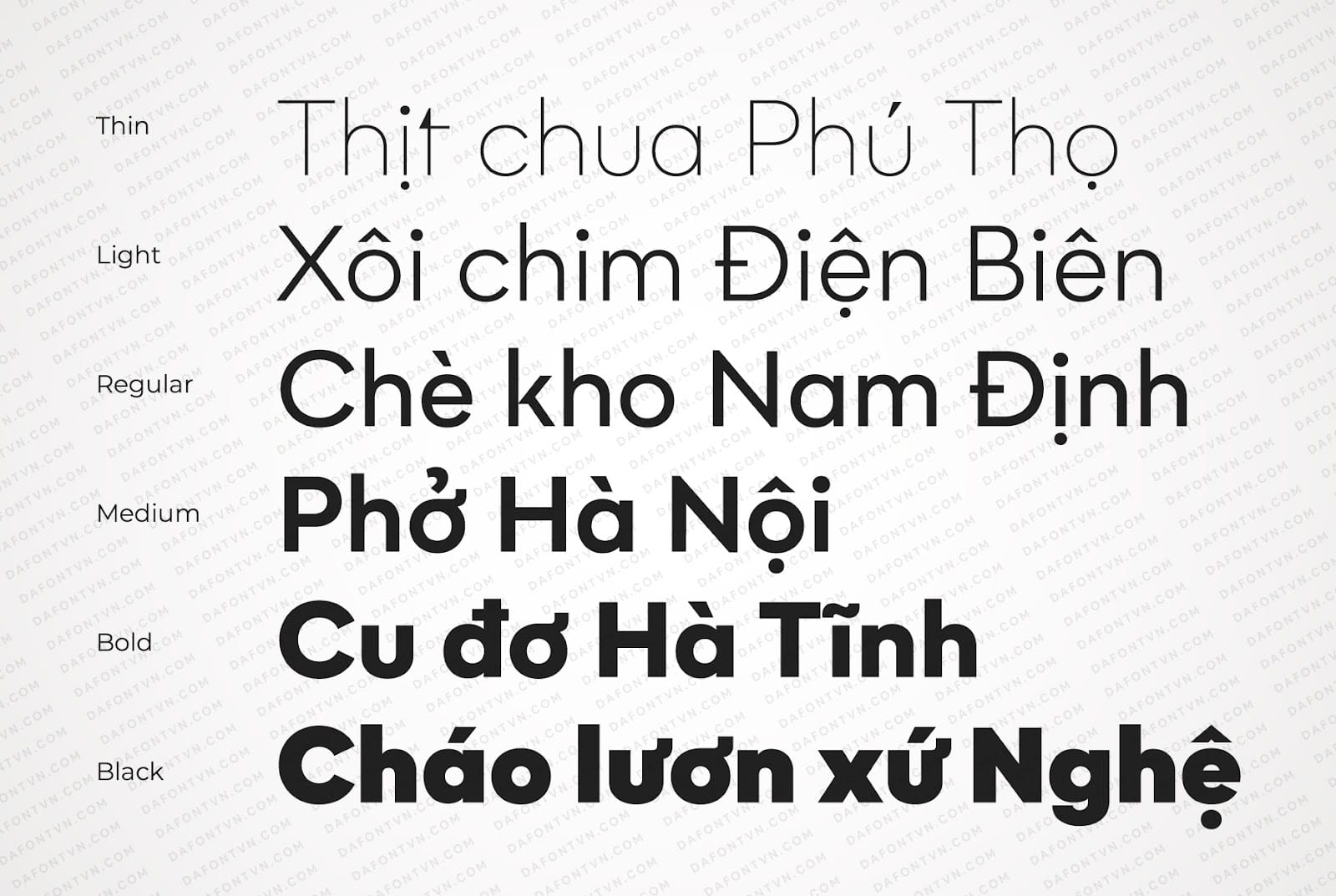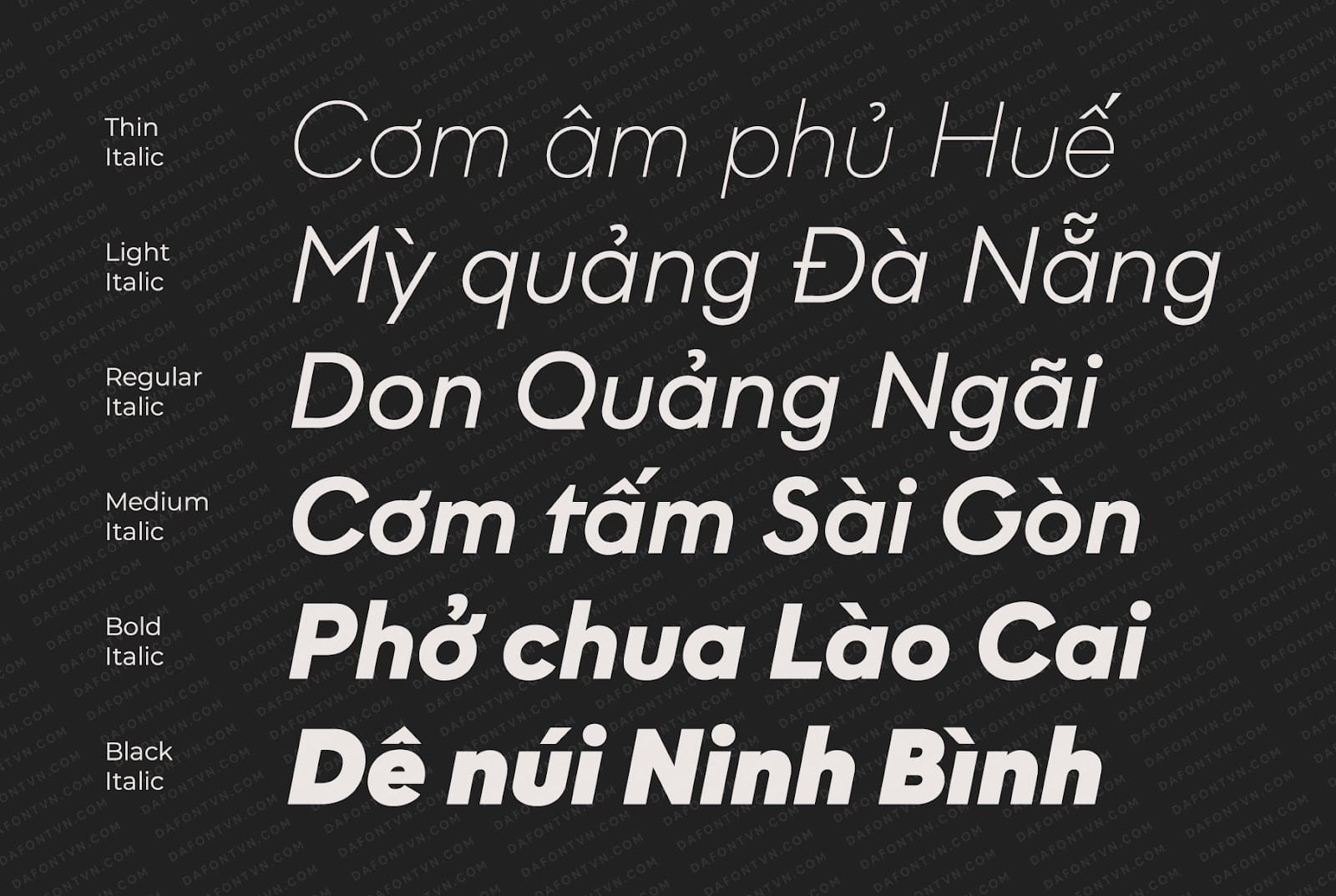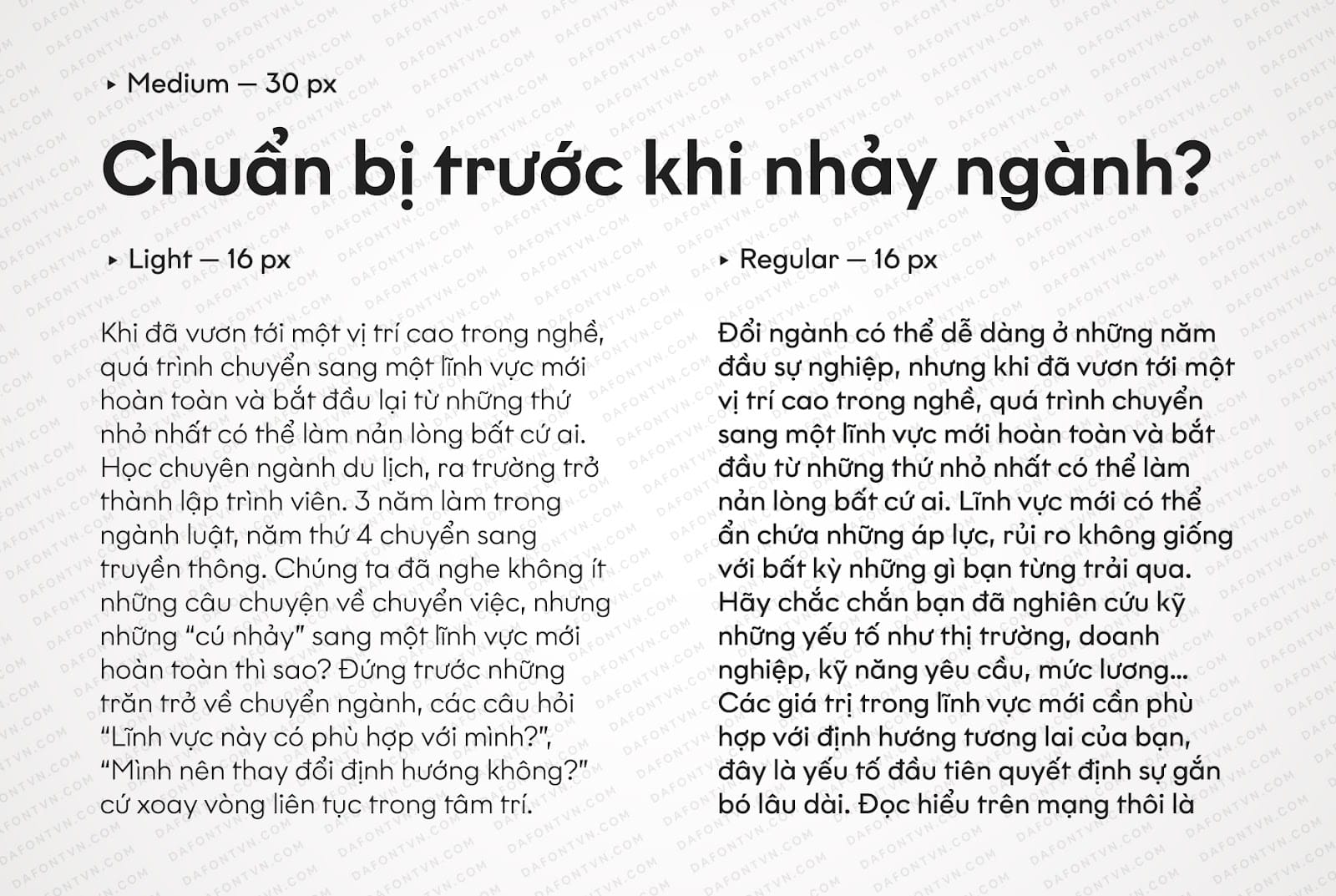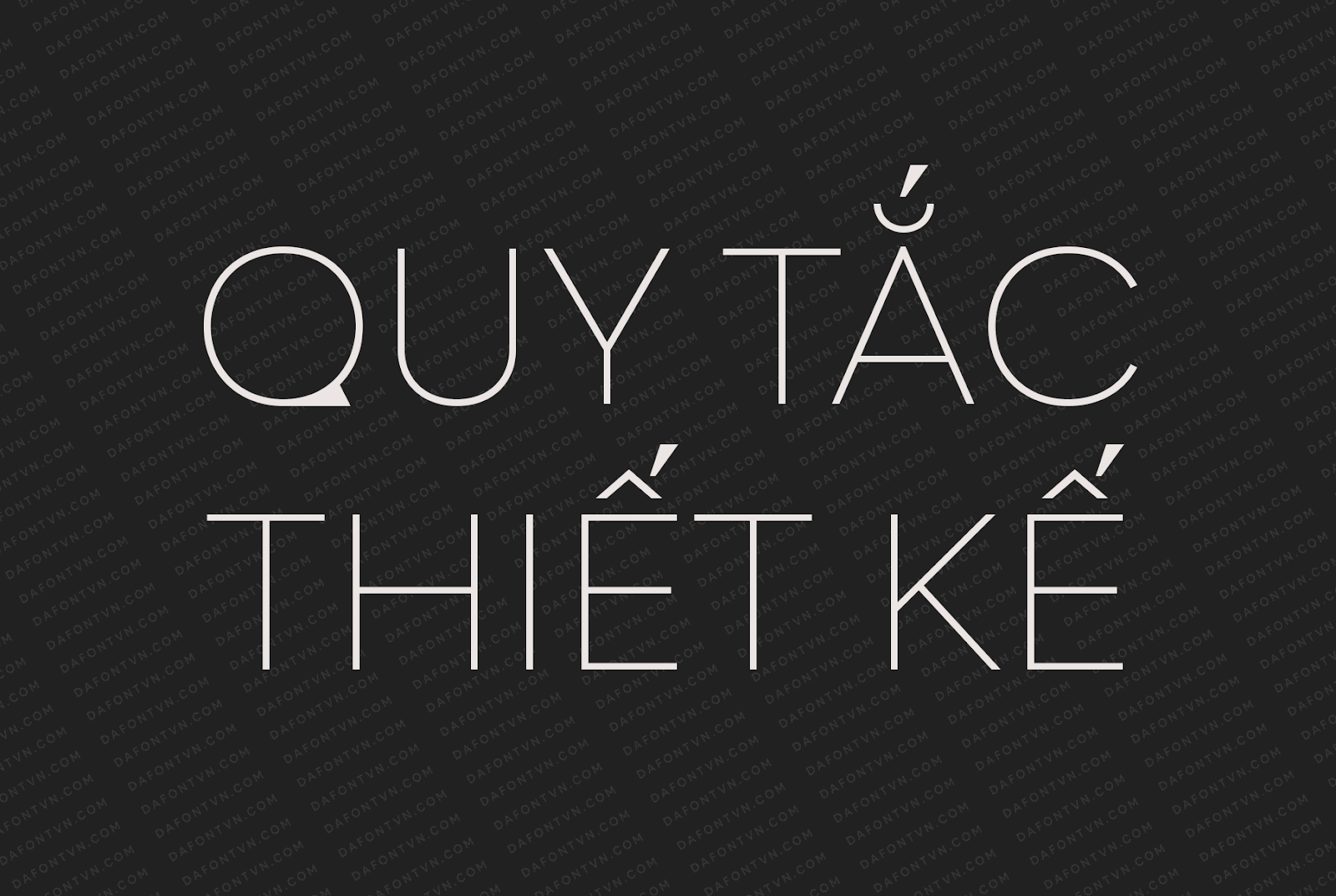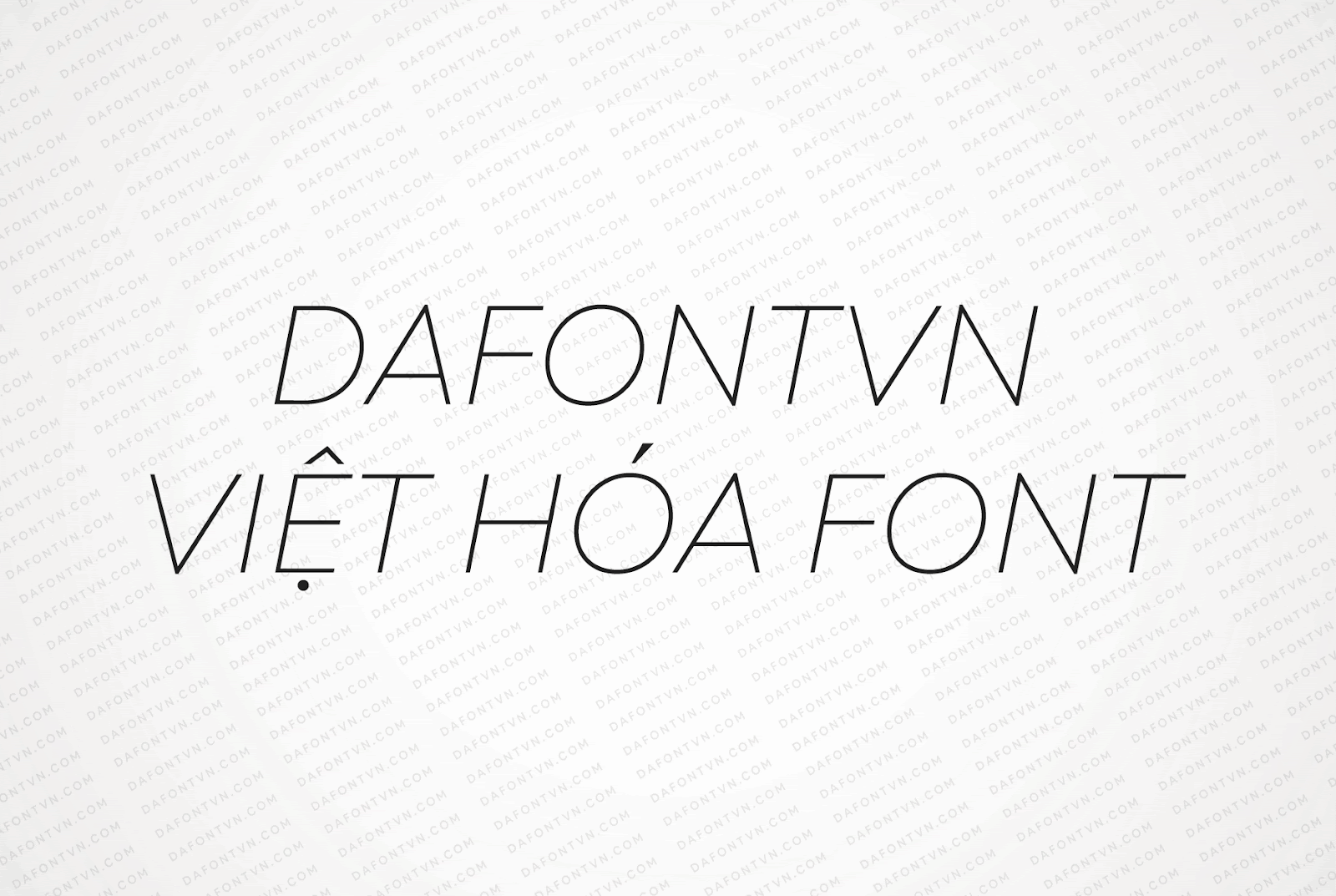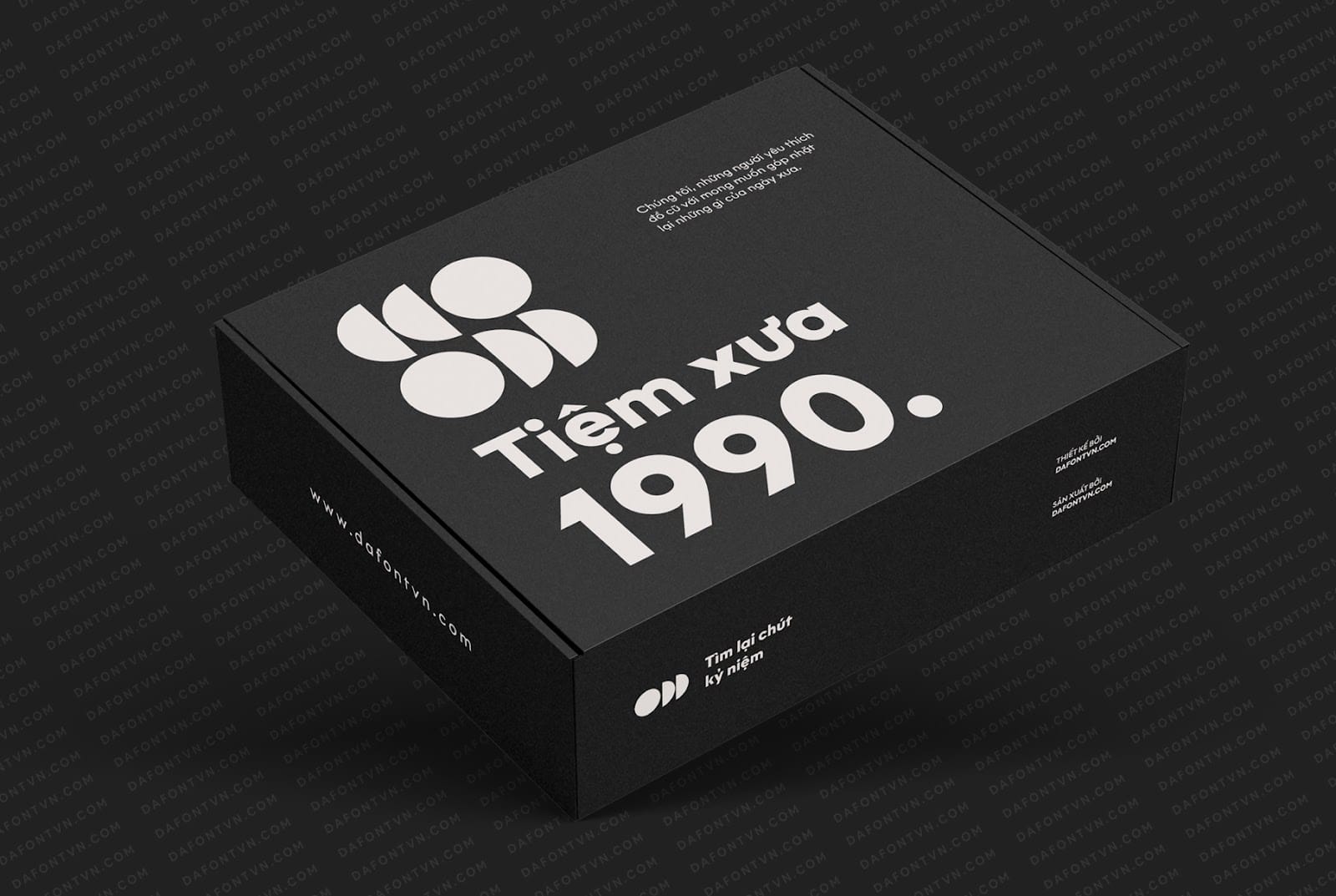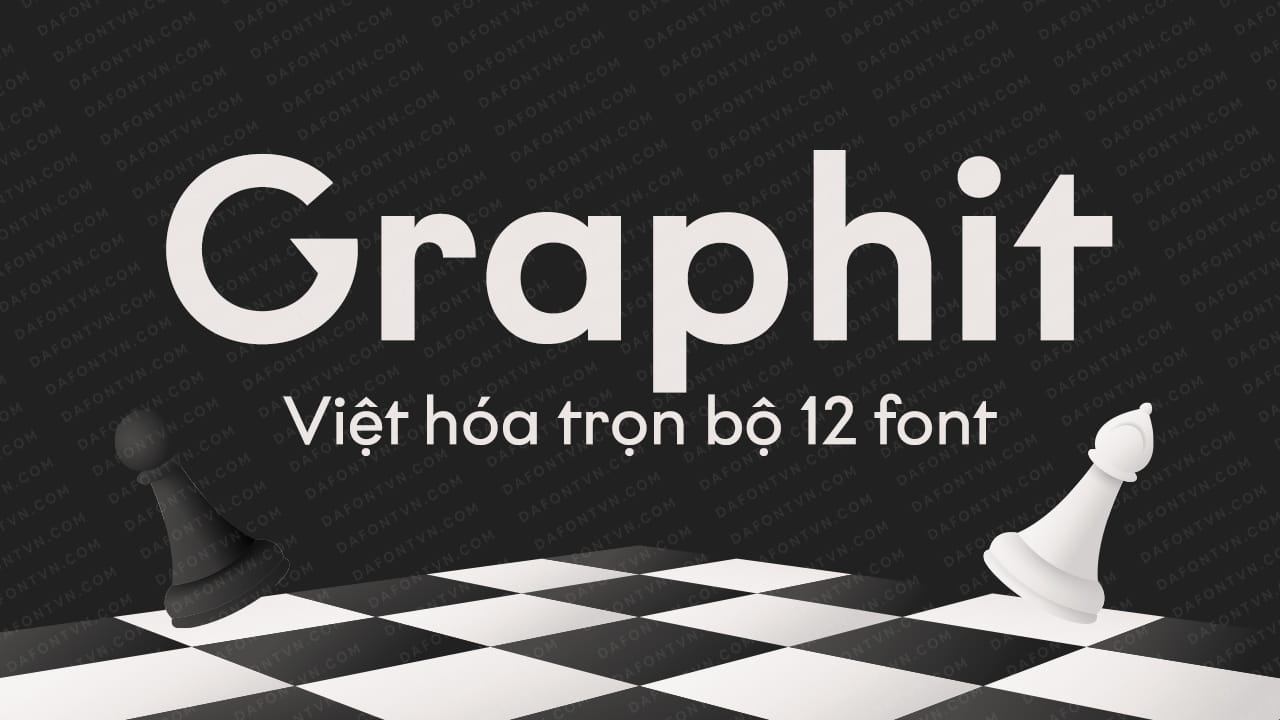
Graphit Font Family là một bộ font sans-serif có 12 font. Các hình dạng hình học cùng với các chi tiết được chế tạo cẩn thận mang lại vẻ ngoài hiện đại và thanh lịch, đồng thời làm cho Graphit phù hợp khi sử dụng làm tiêu đề cũng như nội dung văn bản.
Graphit bao gồm 6 trọng lượng có độ tương phản thấp, từ Thin đến Black cộng với đó là 6 kiểu nghiêng phù hợp cho mỗi trọng lượng. Mỗi chữ cái được tạo ra để truyền tải nhiều cá tính hơn và in sâu vào thông điệp một cảm giác cụ thể. Với một loạt các tính năng typographic, kiểu chữ này tạo điều kiện dễ đọc và rất phù hợp cho việc biên tập, quảng cáo, tiêu đề và sử dụng trên web.
Bộ font được việt hóa đầy đủ, kerning, chỉnh sửa và tối ưu hóa lại. Ngoài ra các ký tự thay thế cũng đã được việt hóa, các bạn có thể sử dụng thông qua tính năng OpenType.